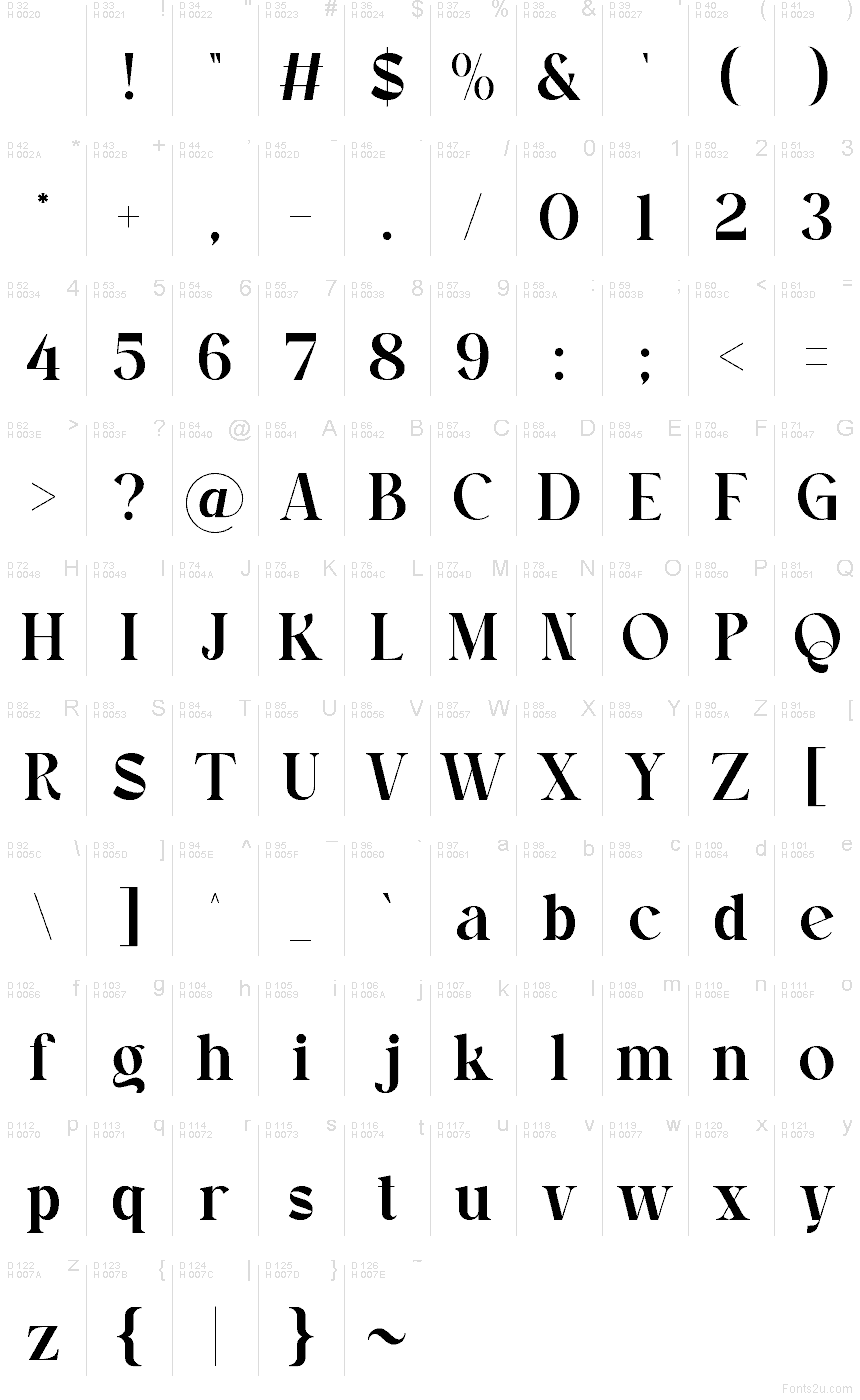
Ralons, da Ermedia, é uma fonte com serifa gratuita de alto contraste, caracterizada por hastes verticais encorpadas, curvas ultrafinas e detalhes marcadamente afilados que conferem às letras um visual de editorial de moda. As letras arredondadas exibem uma ênfase vertical pronunciada.
Tanto títulos de revistas de moda quanto embalagens de perfumes aproveitam sua combinação de curvas amplas e cantos precisos, unindo a expressividade editorial ao acabamento de um produto de luxo. Em convites para eventos formais, as serifas finas proporcionam uma delicadeza que complementa os traços mais grossos.